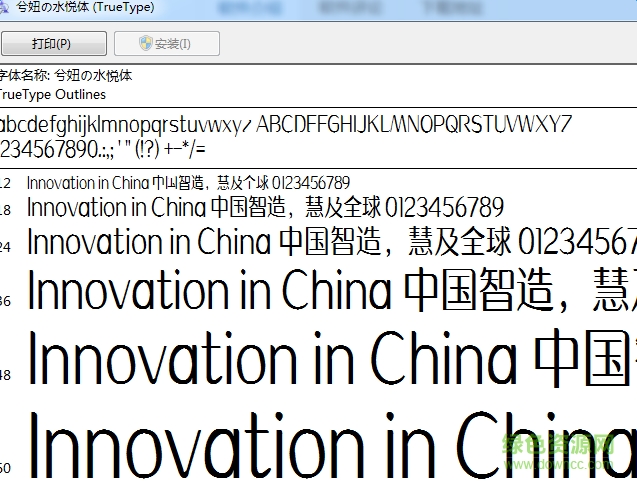
兮妞水悅體
兮妞水悅體字體是一款應(yīng)用于創(chuàng)意設(shè)計(jì)方面的中文字體,該字體線條粗細(xì)適中,字形端正大方得體呈長(zhǎng)條形,整體效果非常的出色,且字庫(kù)完整,可以廣泛應(yīng)用于廣告設(shè)計(jì)、宣傳海報(bào)、ppt、影視制作以及任何使用文字的領(lǐng)域,有需要的朋友可以免費(fèi)下載收藏。
兮妞水悅體字體是一款極具個(gè)性的字體,改字體粗細(xì)得當(dāng),彰顯了自己的個(gè)性,有喜歡的朋友可以來綠色資源網(wǎng)下載使用!